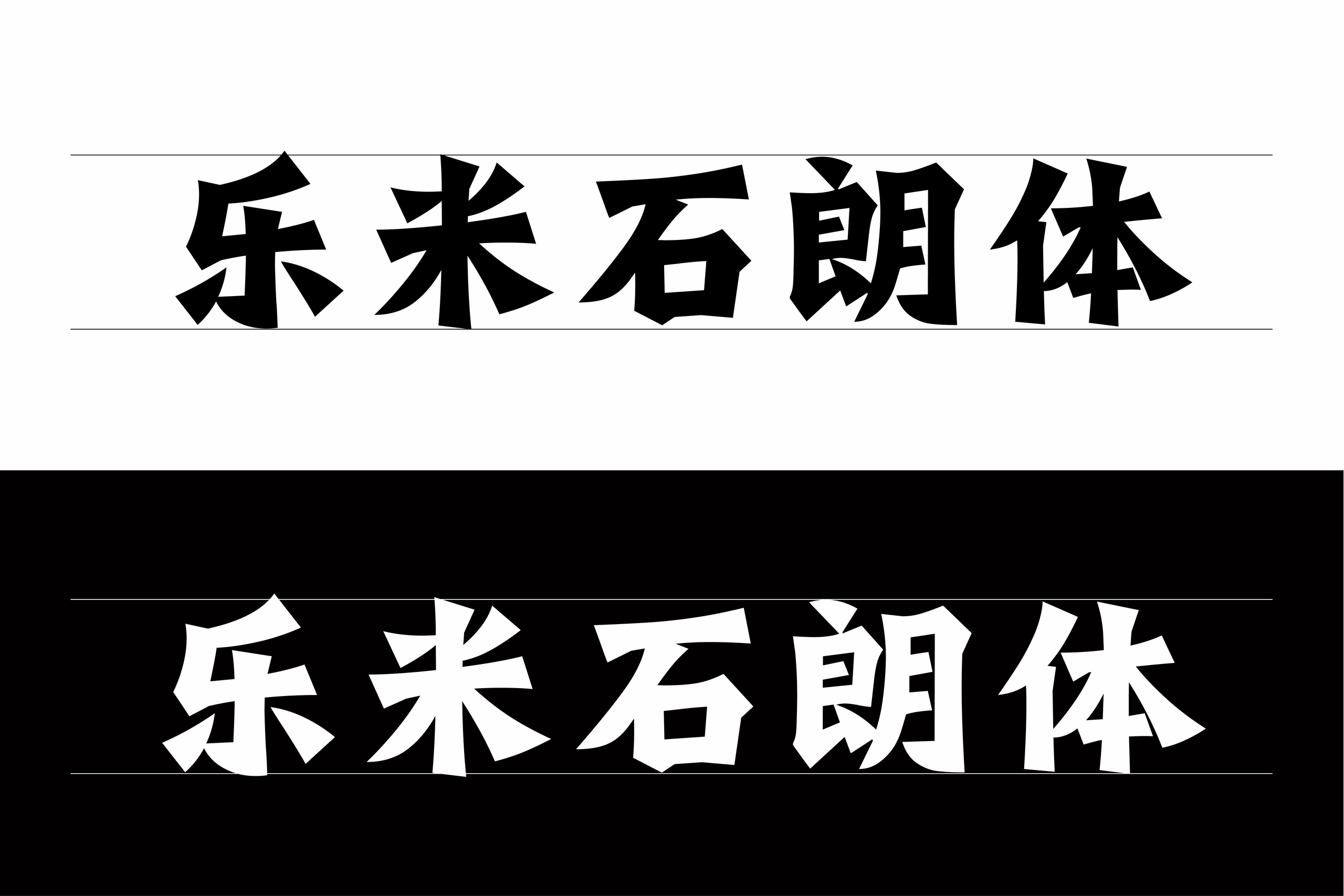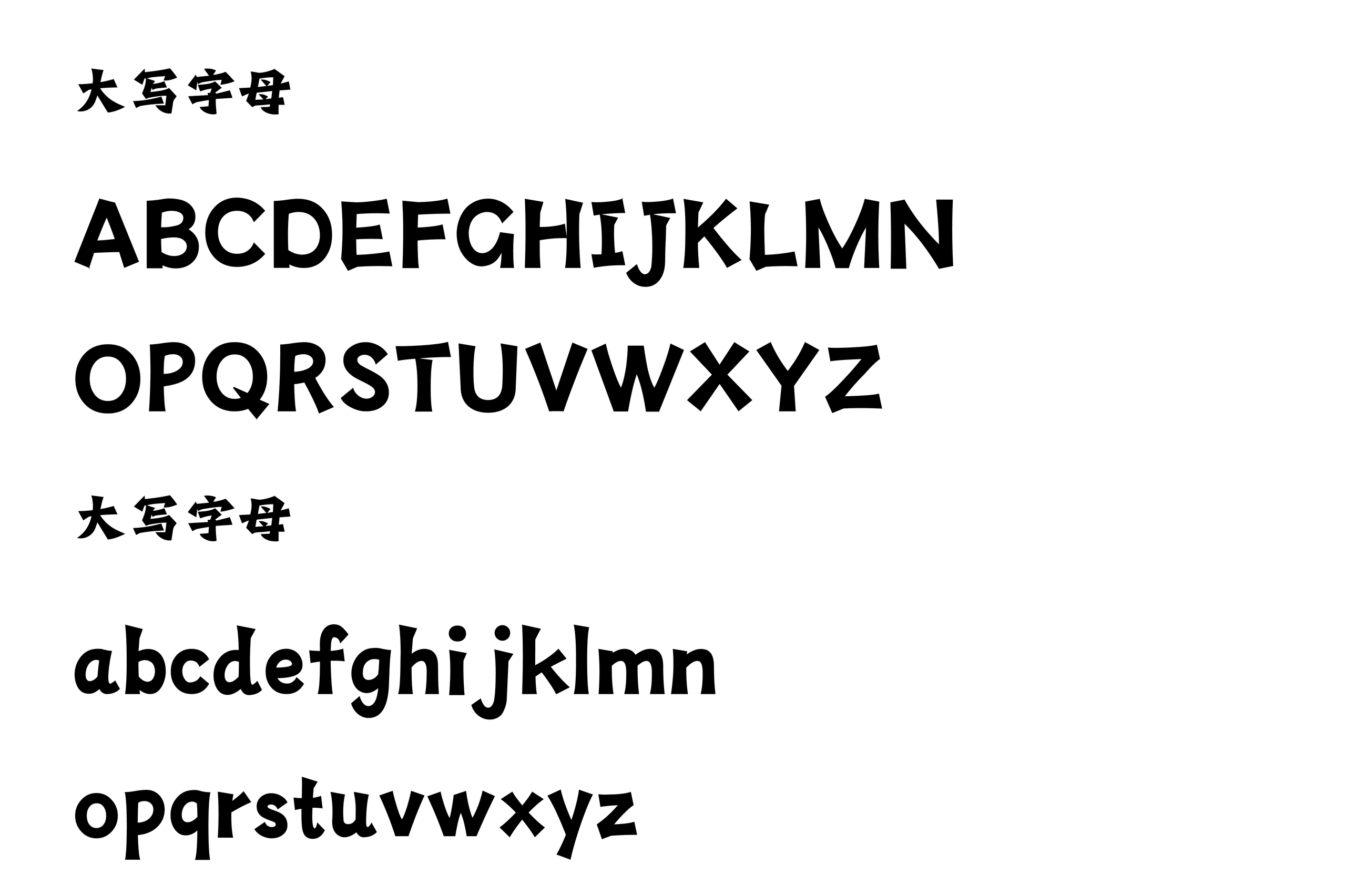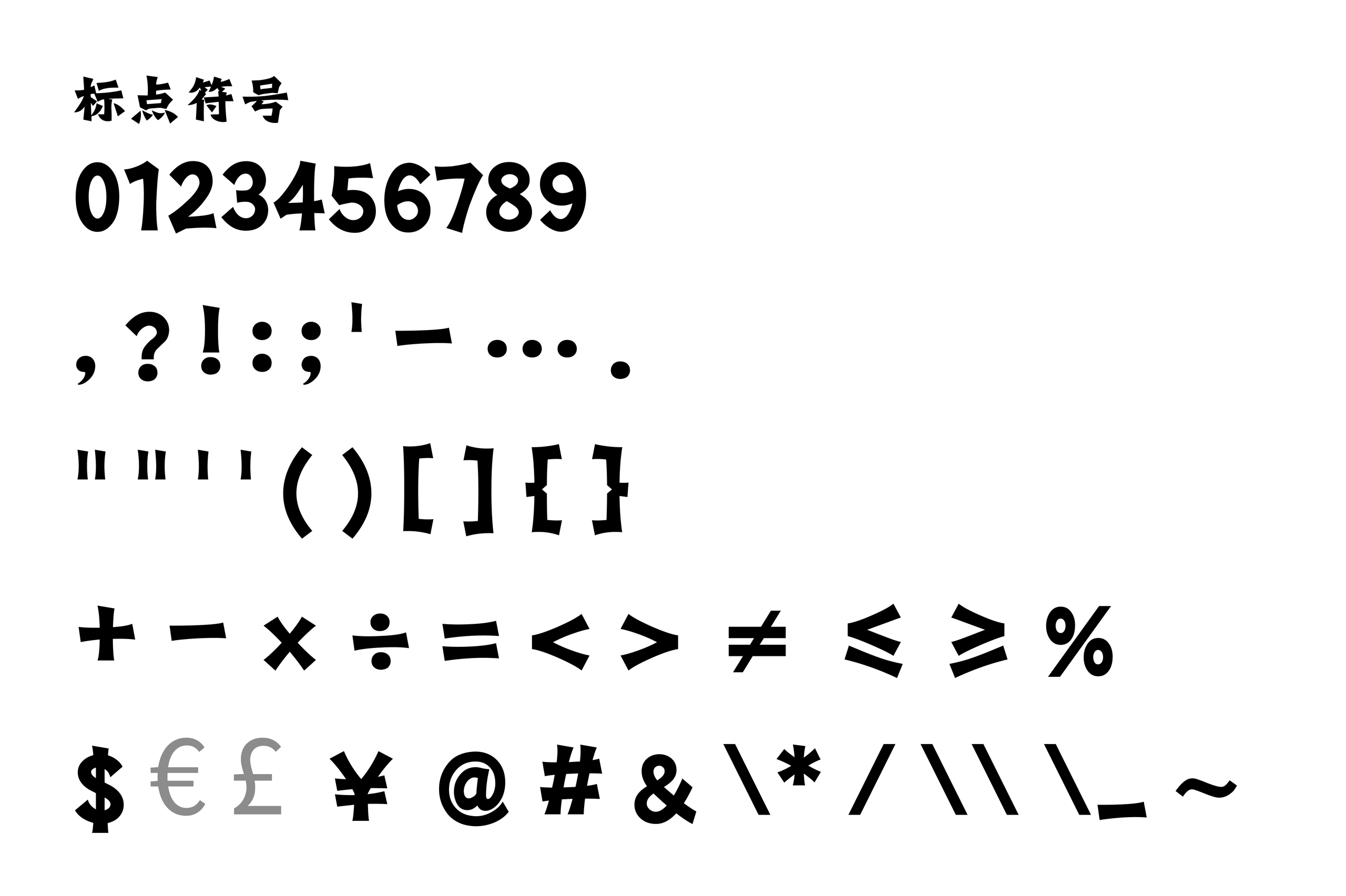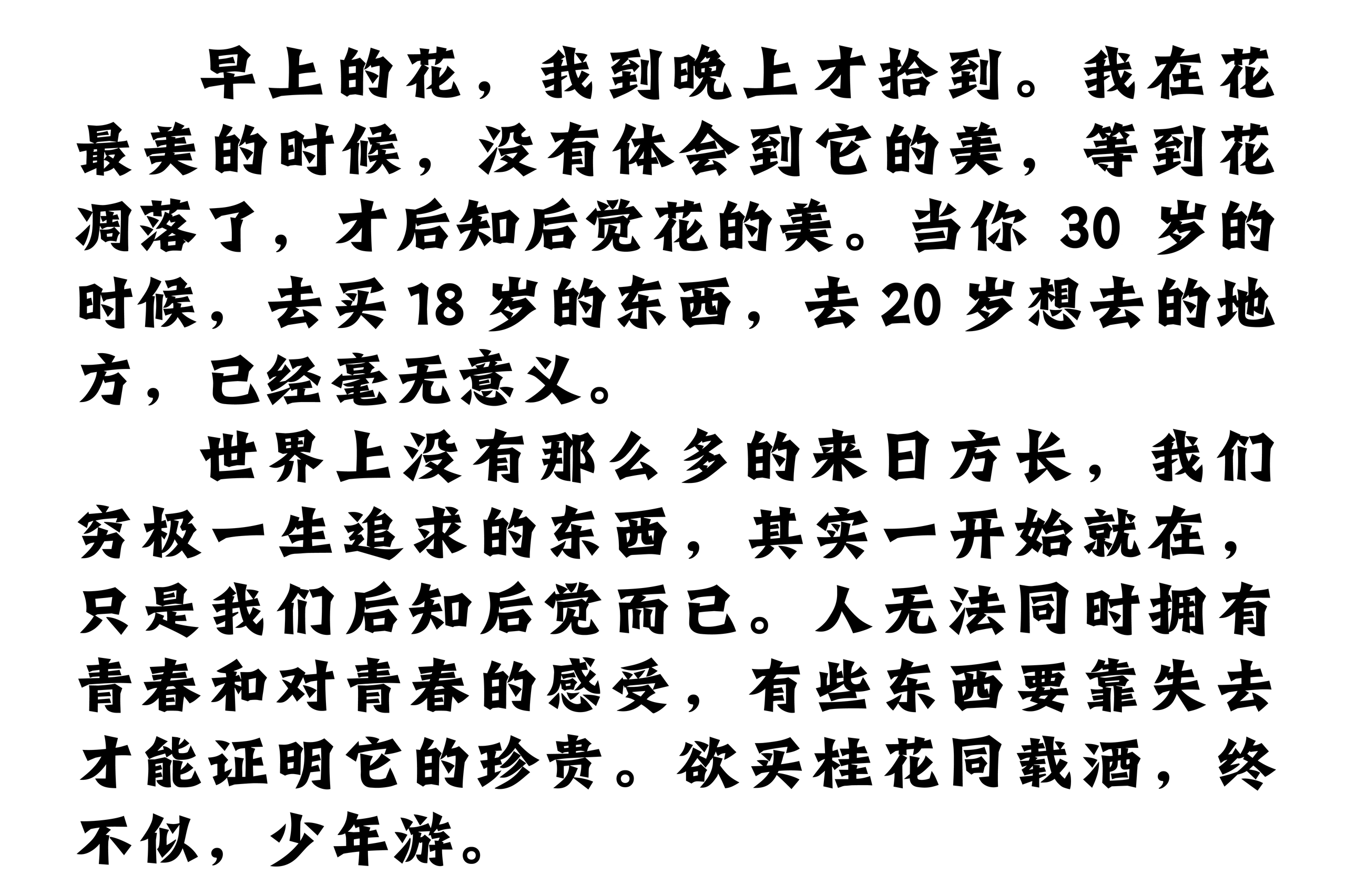
乐米石朗体
乐米石朗体是一款由杭州乐米网络科技有限公司发布,并提供免费商用授权的中文字体。字体以鲜明的几何切角和富有张力的笔画造型为主要视觉特征,在汉字结构中融入较为大胆的斜切与折角处理,使整体字形呈现出硬朗、利落且具有现代感的视觉气质。
从字形表现来看,乐米石朗体并没有沿用传统黑体规整、均衡的笔画逻辑,而是通过明显的尖角、斜面以及不规则的笔画收尾,让文字拥有更强的造型感。部分笔画在转折处形成具有辨识度的切面,横竖之间也呈现出更加直接的力量关系,使汉字在保持基本结构识别度的同时,获得更鲜明的个性表达。
字体的整体重心较为稳健,粗壮的笔画赋予文字较强的视觉分量,而局部夸张的切角又打破了传统字体的严谨秩序。这种“厚重结构+锐利细节”的组合,让乐米石朗体既具有较强的冲击力,又不会完全脱离中文字体本身的阅读逻辑。
在英文字符部分,乐米石朗体同样延续了中文字体的设计语言。大写字母采用较为厚实的结构,并加入明显的斜切、折角和不规则细节;小写字母则在圆润与锐利之间形成对比,使中英文混排时能够保持相对统一的视觉风格。整体英文字符更偏向展示型设计,适合用于需要强化视觉个性的标题与短文本。
从应用场景来看,乐米石朗体更适合发挥其造型感强、辨识度高的特点,可用于品牌标题、活动海报、潮流视觉、包装设计、短视频封面、展览主题、广告标题以及个性化宣传物料等场景。尤其是在大字号展示环境中,字体独特的切角和厚重笔画能够形成较强的视觉焦点,让标题更容易从画面中突出出来。
总体而言,乐米石朗体是一款具有明显视觉个性的创意中文字体。它通过切角、折线和厚重笔画重新处理汉字的视觉形态,在传统文字结构与现代几何设计之间建立起独特的平衡。对于希望摆脱常规黑体的规整感,同时又需要一款具有较强力量感和辨识度的中文字体的设计者来说,乐米石朗体是一个值得关注的选择。